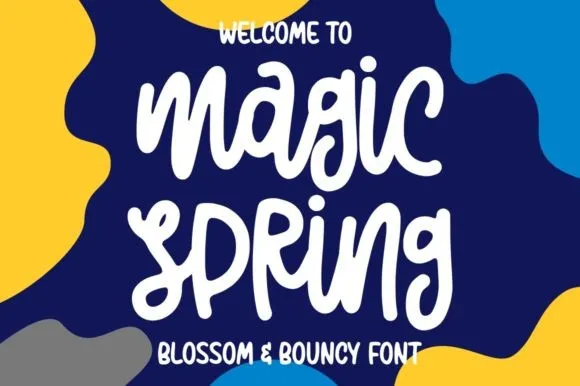
Magic Spring Script Font – Download Grátis
Introduzimos Magic Spring Script Font, uma fonte escrita à mão que combina uma textura monoline com um estilo desenhado a mão, oferecendo letras vibrantes e divertidas para celebrar o mais encantador dos períodos do ano: outono. Esta elegante fonte de script é perfeita tanto para projetos de design social como para criações impressas ou até mesmo em designs digitais, desde posts na sua página de Instagram até a etiqueta de uma camiseta ou adesivo. Magic Spring Script Font é perfeito para qualquer projeto que você esteja realizando. Suas letras quirk e vivas podem dar um toque especial aos seus trabalhos, tornando-os verdadeiramente chamativos e únicos. É uma fonte versátil que se adapta a diversos usos, incluindo logos, sinalizações, stickers, artigos em SVG, camisetas, mugs e muito mais. Seja você um criador de conteúdo para redes sociais ou um designer gráfico buscando uma fonte única para seus projetos impressos, Magic Spring Script Font certamente será a escolha perfeita.